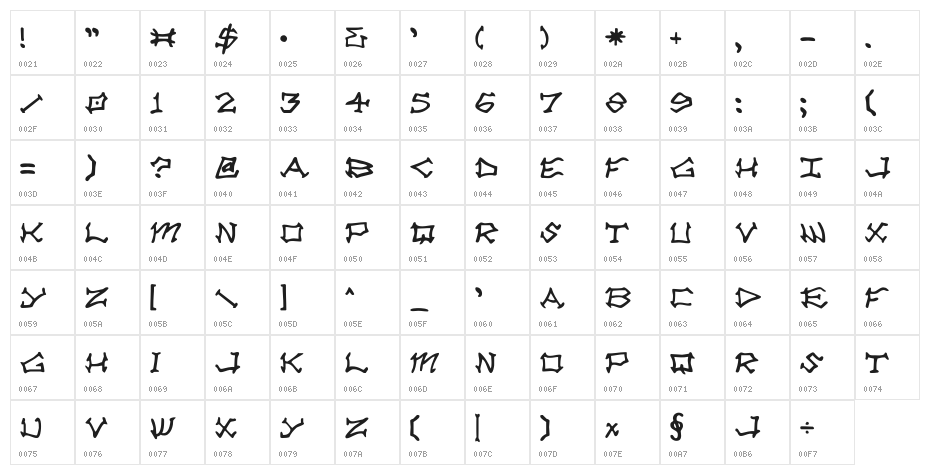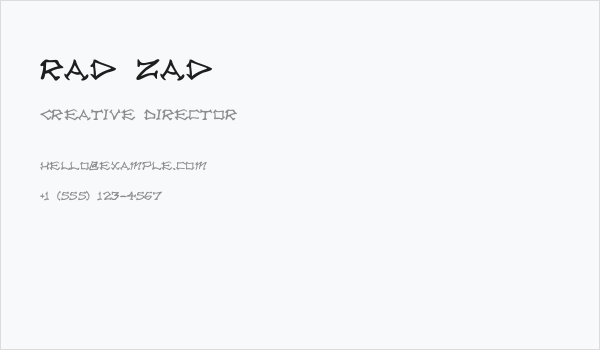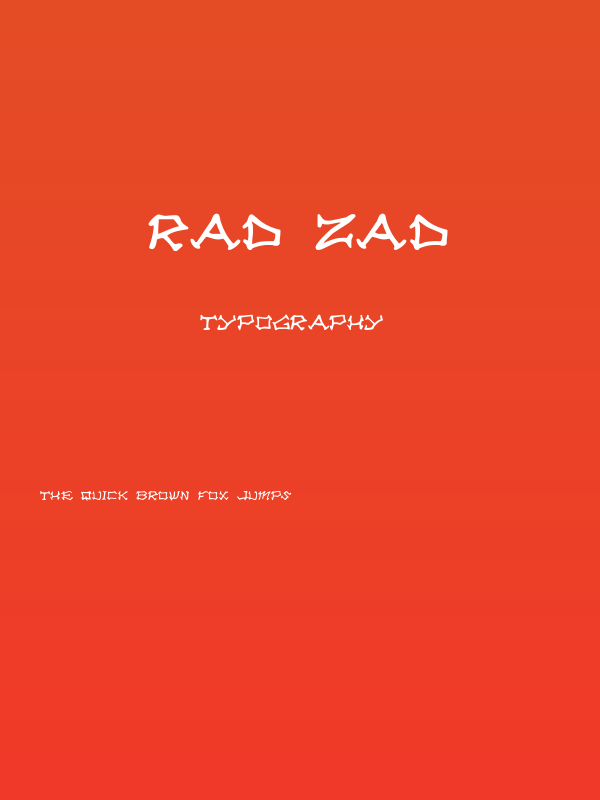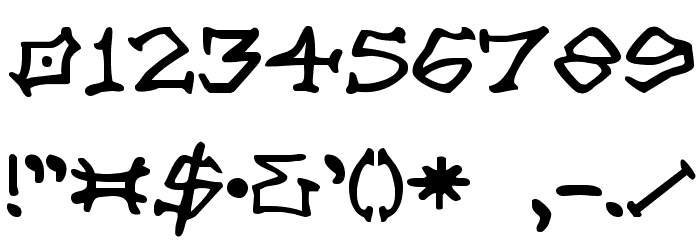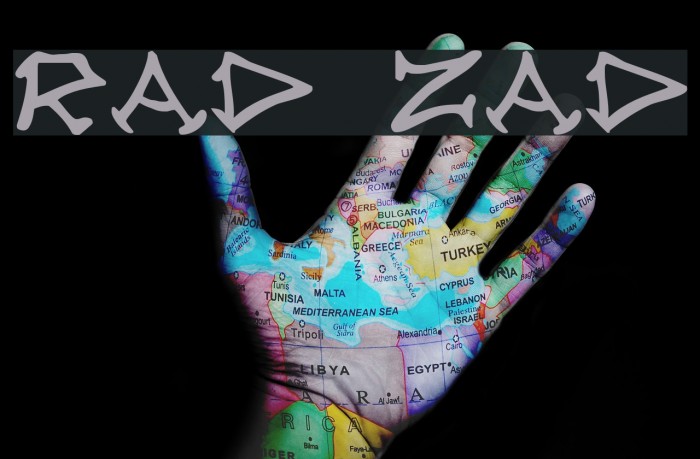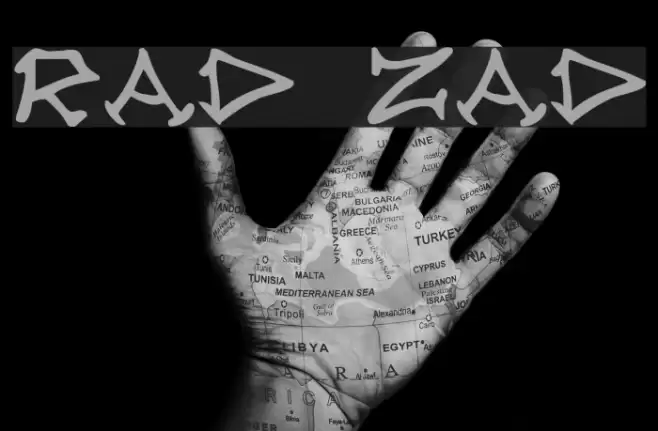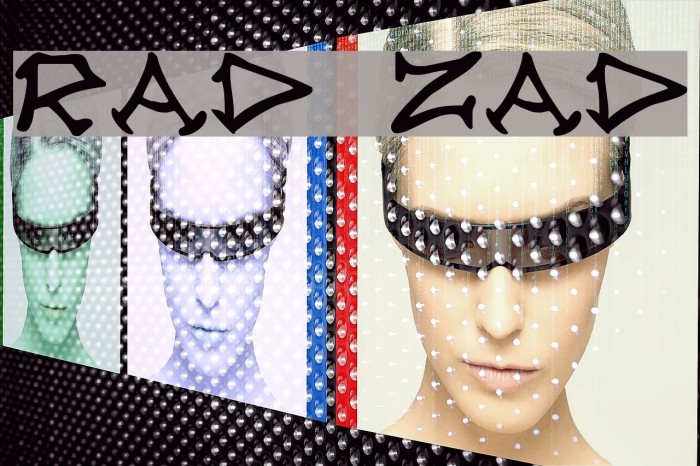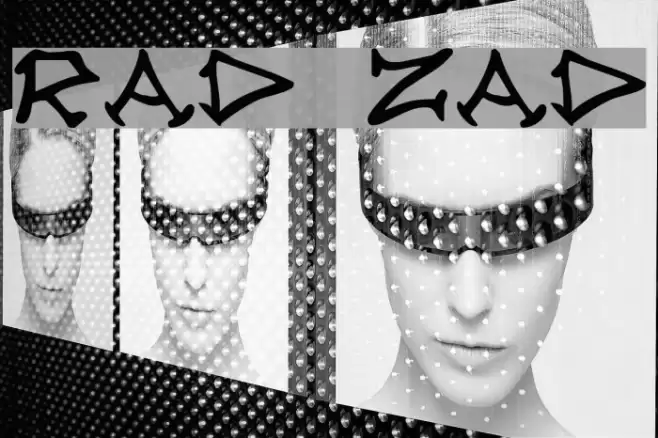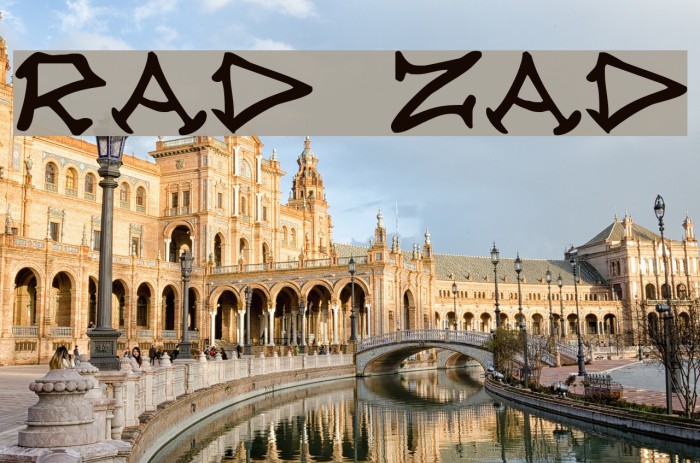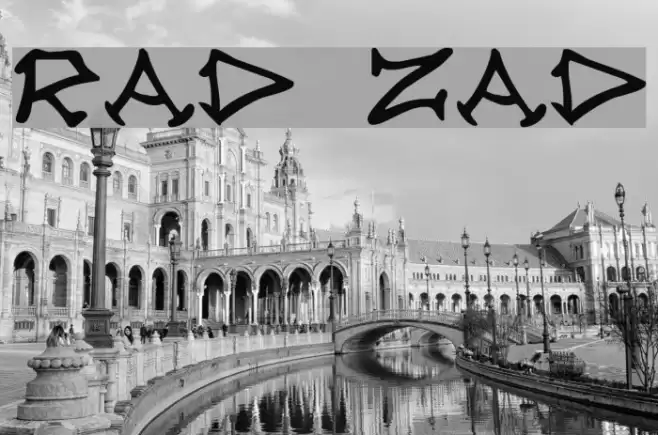
Rad Zad Font
| 全体的なスタイル | Modern, Urban, Artistic |
| おすすめプロジェクト | Ideal for street art designs, music album covers, urban-themed posters, and edgy branding projects. |